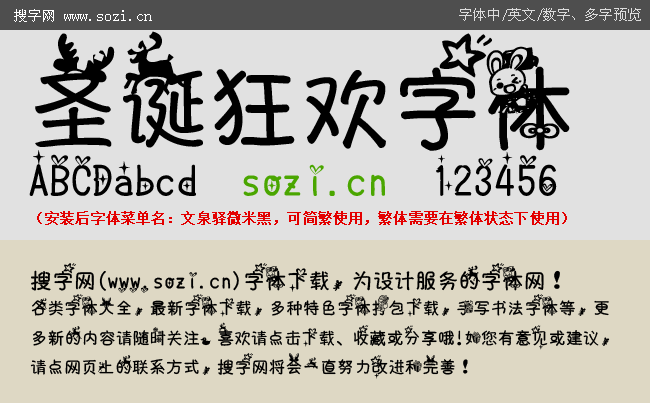
圣誕狂歡字體
搜字網(wǎng)給大家提供一款卡通手寫風(fēng)格的手機中文字體下載。名字叫圣誕狂歡字體,這款手機字體是仿照兒童手寫風(fēng)格的卡通手寫字體,結(jié)構(gòu)帶有POP字體風(fēng)格,字體間還插入有趣的卡通圖案,特別適合喜歡手機字體個性一些的朋友在手機上安裝使用。